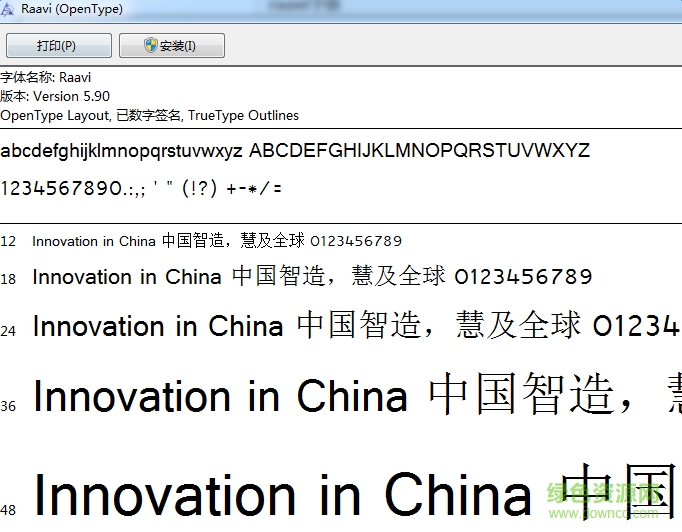
raavi字體是一款極具個(gè)性的英文字體,該字體可以廣泛應(yīng)用于包裝印刷、企業(yè)LOGO、宣傳海報(bào)、ppt、影視制作以及任何使用文字的領(lǐng)域,有需要的朋友可以免費(fèi)下載收藏。
raavi字體是一款英文字體庫中的個(gè)性字體,該字體線條粗細(xì)適中,給人一種非常舒適的感覺。有喜歡的朋友就來綠色資源網(wǎng)下載使用吧!